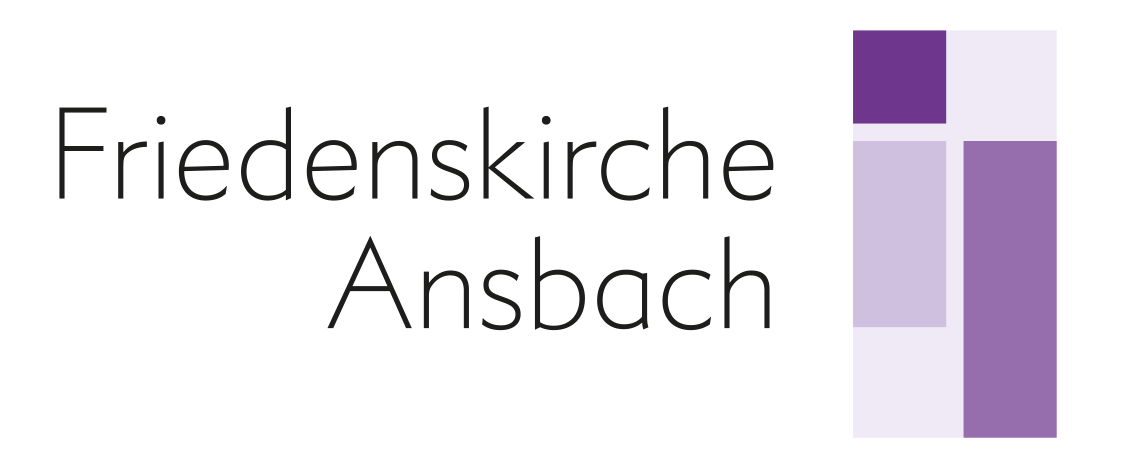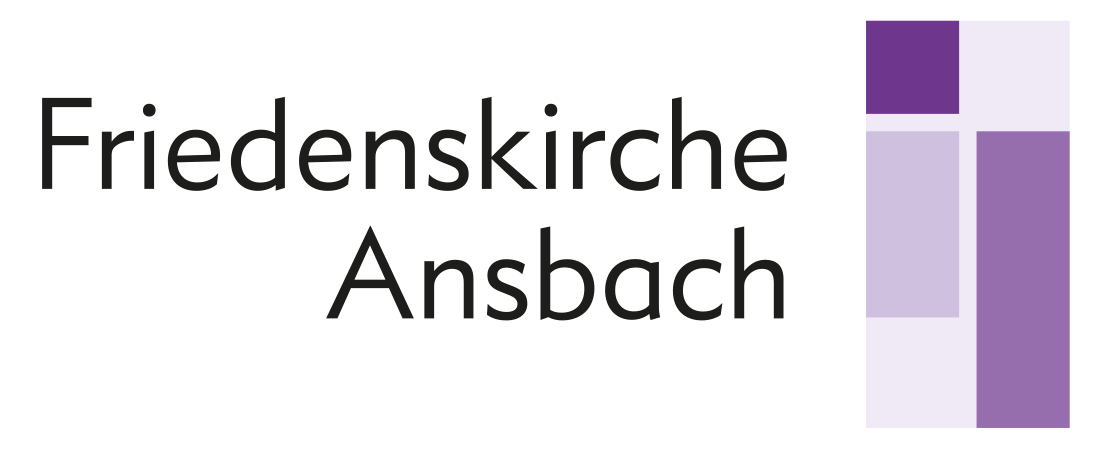
Zeichnung vektorisieren
Die Proportionen des Kreuzes. Es wirkt auf mich eher wie ein Antennemast. Kalt und technisch. Stählern. Wenn das das Kreuz sein soll, an das Christus geschlagen wurde, hätten die Römer sich bei der Kreuzigung anseilen müssen. Und sie hätten Christus anschrauben müssen. Christus wird durch die Proportionen des Kreuzes unerreichbar. Stünde man vor dem Kreuz, hätte man Mühe, die Füße des Gekreuzigten zu berühren. In den Proportionen liegt eine kalte Brutalität, die durch die Wahl der Farben noch betont wird. Und Christus selbst hätte es wahrscheinlich auch nicht bis nach Golgatha tragen können, weil er damit nicht durch die Kurven enger Gassen gekommen wäre. Kurz gesagt: Es ist nicht gerade ergonomisch.
Ich kann das nicht nachvollziehen. Antennenmast? Ich meine mich zu erinnern, auch schon Bilder gesehen zu haben, auf denen Jesus ein extrem langes Kreuz geschleppt hat. Und hat man Jesus nicht erst am liegenden Kreuz befestigt (egal ob mit Nägeln, Schrauben oder Stricken) und das Kreuz dann erst aufgerichtet? Ich weiß es nicht. Aber darum geht es ja auch gar nicht, denke ich. Und das Logo reduziert sich für mich überhaupt nicht auf die mehr oder weniger naturgetreue oder »ergonomische« Darstellung. Auch wenn ein Kreuz darin wohl erkennbar ist, so dominiert das für mein Auge nicht, sondern das schwingt eben nur mit.
Zur Schrift: Die Metro Nova ist die Brotschrift des Gemeindebriefs, deshalb lasse ich sie auch im Logo. Sie lässt übrigens über eine Formatsatz-Einstellung auch einige andere Zeichenformen zu, unter anderem ein gerades e. Und Du hast Recht, es wäre eine Überlegung wert, das zumindest in Verbindung mit dem Logo entsprechend zu ändern.
Mein Eindruck ist, dass tatsächlich ein paar eigens auf Eure Bedürfnisse zugeschnittene Entwürfe nicht schaden könnten.
Ich wollte ja auch wissen, ob es überhaupt Sinn macht, auf der Basis eines der Fotos da mit Illustrators Nachzeichnen-Funktion ranzugehen – da sehe ich jetzt, dass es nicht nur an meiner Unfähigkeit lag, sondern dass ein Vektorisieren in dem Fall eher ein Selber-Machen wäre, bei dem das Foto nur als Vorlage dienen würde. (Das wäre natürlich eine Gelegenheit, etwas in Illustrator einzusteigen.) Die Illustrator-Automatik käme wohl nur in Frage, wenn man eine der Zeichnungen entsprechend vorbereitet und Illustrator dann darauf loslässt.
Ich kann Arno schon folgen und bekomme die Metro formal auch nicht mit der Bildmarke zusammen. Da macht sich die etwas eckigere Rotis in meinen Augen schon etwas besser.
Die Rotis ist ja auch die Schrift der Landeskirche in Bayern. Aber die will der Pfarrer auf keinen Fall.
Und hat man Jesus nicht erst am liegenden Kreuz befestigt (egal ob mit Nägeln, Schrauben oder Stricken) und das Kreuz dann erst aufgerichtet?
Ja. Anders hätte sich das nicht bewerkstelligen lassen. Ich habe frei assoziiert. Soweit ich weiß, erfolgte die Befestigung auch nicht mit Nägeln, sondern schlichtweg mit Seilen. Der Gekreuzigte verblutet auch nicht, sondern erstickt. Ich könnte mir aber vorstellen, dass bestimmte Verurteilte auch an das Kreuz genagelt wurden. (Das ist offenbar belegt.)
Kennst du den Film »Die letzte Versuchung Christi«? Christus zimmert die Querbalken für die Römer, um sich bei Gott unbeliebt zu machen. Er trägt diese Querbalken der zum Tode durch Kreuzigung Verurteilten zur Hinrichtungsstätte. Er fühlt sich von Gott berufen und will der Bürde dieser Berufung entgehen, indem er mit den Römern kollaboriert. Der Film steht auf dem Index der Katholischen Kirche, soweit ich mich erinnere (was ich übrigens absolut nicht verstehen kann). Jedenfalls ähnelt das Kreuz eher dem Buchstaben T. Der Stamm des T ist oben abgeflacht und der Querbalken enthält eine entsprechende Lücke und wird einfach auf den Balken aufgesetzt. Ich finde das ziemlich plausibel. Aber natürlich schlage ich kein T als Alternative vor.
Auch die Rolle des Judas ist eine ganz andere als die, die die Bibel vermittelt. So ist zum Beispiel der Satz »In dieser Nacht […] wirst du mich dreimal verleugnen« nicht als Prophezeiung, sondern als Auftrag Christi an Judas zu verstehen. Christus braucht Judas, um zum Märtyrer werden zu können.
Worauf ich hinaus wollte, ist aber, dass ein solch langes Kreuz Christus von den Menschen entfernt. Es brächte ihn näher zu Gott als den Menschen. Und auf mich wirkt es sehr kalt. Das sind doch nicht die Botschaften, die eine moderne Kirche vermitteln will, oder?
Das war aber nicht Judas, sondern Petrus, als Peter sollte ich das wissen...
Petrus aber sagte zu ihm: „Wenn auch alle anderen zum Straucheln gebracht werden, so doch ich nicht.“ Darauf sprach Jesus zu ihm: „Wahrlich, ich sage dir: Selbst du wirst mich heute, ja diese Nacht, bevor ein Hahn zweimal kräht, dreimal verleugnen.“
Aber auch ich bin der Meinung, dass dieses negative Bild des geldgierigem Verräters bei Judas auch nicht so stimmig ist, und der (schließlich war er Jesu engster Vertrauter und Kassenführer der Gruppe) sehr wohl den Auftrag hatte, die Obrigkeit zu verständigen. Wäre Jesu da nur von Mob gelyncht worden, wäre der ganze Märtyrer-Plan nicht aufgegangen.
Ob das gelungen ist oder nicht, mag ich hier nicht kommentieren. Aber Kirchenlogos mit ausschließlich "ergonomischen" Kreuzen fänd ich gruselig.
Das kann aber durchaus lebhaft, bunt und fröhlich daherkommen –
Ja, aber das sind keine Zeichnungen mehr, wie man sie sehr oft findet. Bei den Bespielen ist der Abstraktionsgrad schon sehr hoch. Mosaike werden oft genutzt, um zu zeigen: "Kirche besteht aus Vielen", oder "Menschen bilden diese Gemeinde", das kann sehr sinnstiftend sein.